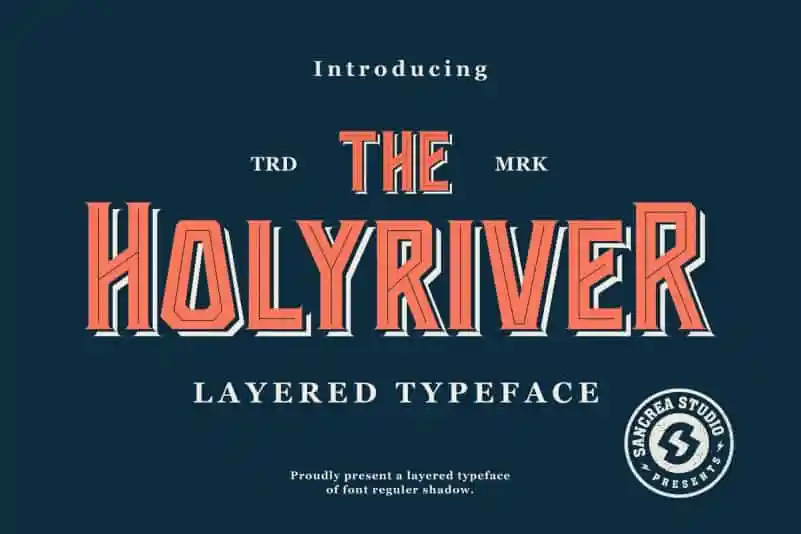
A Holyriver Display Font é uma opção ideal para estilos visuais que buscam criar uma atmosfera nostálgica e vibrante. Essa fonte apresenta um sabor retro forte, perfeita para uso em grandes tamanhos de texto e com cores cintilantes, combinando bem com desenhos geométricos fortes para destacar sua presença no design gráfico. Desenvolvida pelo designer sancreastd, a Holyriver é uma fonte composta que se inspira nas famosas bandas de ópera dos Estados Unidos e nos cartazes de circo antigos, conhecidos por suas formas robustas e arredondadas. Ela cria um impacto visual imediato, chamando atenção para detalhes mais próximos ao olhar do espectador. Esta fonte inclui quatro sistemas de fontes que podem ser usados juntos para criar diversas camadas de sombreamento e efeitos visuais sofisticados. Uma excelente escolha para designers buscando capturar a essência da década de 1950 nos seus projetos, seja para aplicativos digitais ou impressão. Esta fonte é uma ótima adição à sua coleção, oferecendo um estilo único e poderoso que se adaptará com facilidade a diversas aplicações visuais.